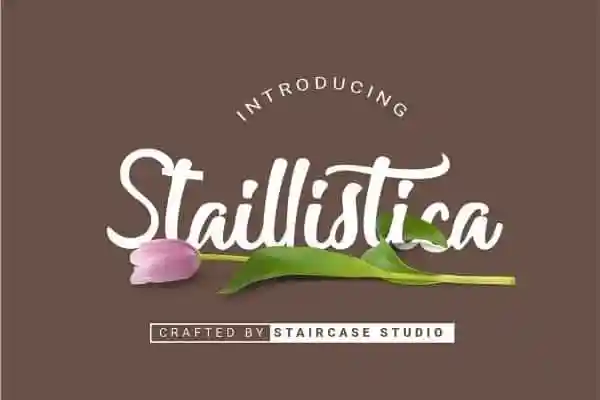
Staillistica Script Font – Download Grátis
Introduzimos uma nova fonte chamada Staillistica Script Font inspirada nos tipos script urbanos com letras afiadas e belas que criam fontes modernas, elegantes e de tendência. Esta font é um trabalho cuidadosamente desenvolvido pela Staircase Studio e agora está disponível para compartilhamento. Composta por uma ampla gama de letras e números, a Staillistica Script Font é perfeitamente adequada às suas necessidades de projeto. Ela se destaca especialmente em aplicativos como Logotypes, Design Corporativo, Design de Logotipo, Arte digital de Letras, T-Shirts/Apparel, Folhetos, Posters, Sinalizações e Design de Anúncios. Além disso, a Staillistica Script Font é ideal para qualquer necessidade de design. Suas linhas elegantes e sua aparência sofisticada tornam-a uma escolha ideal tanto para projetos pessoais quanto corporativos. A Staircase Studio criou um verdadeiro leque de opções de design com esta fonte, que certamente vai transformar seu próximo projeto.